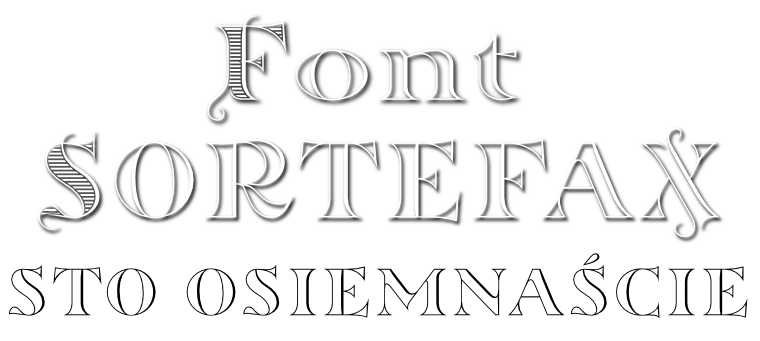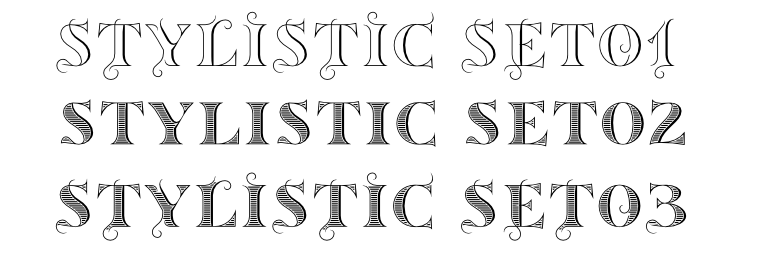
Szeryfowy, pogrubiony font obrysowy Sortefax z dekoracyjnymi zestawami stylistycznymi. Dwa zestawy s01 i s02 dostępne są jako odrębne fonty SortefaxS01 i SortefaxS02.